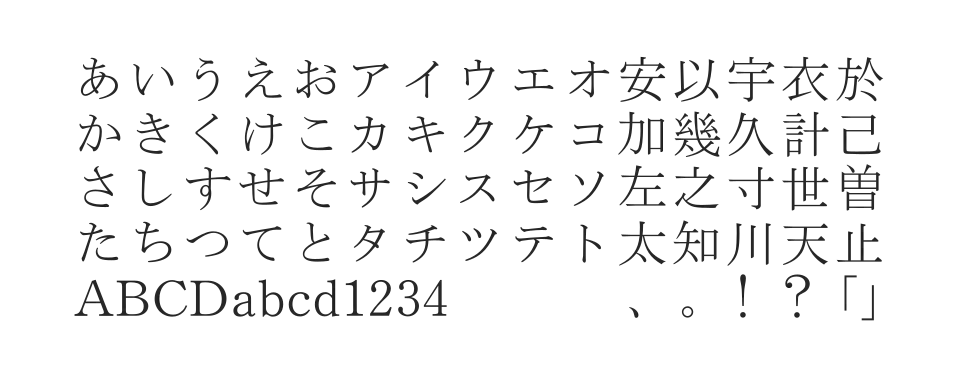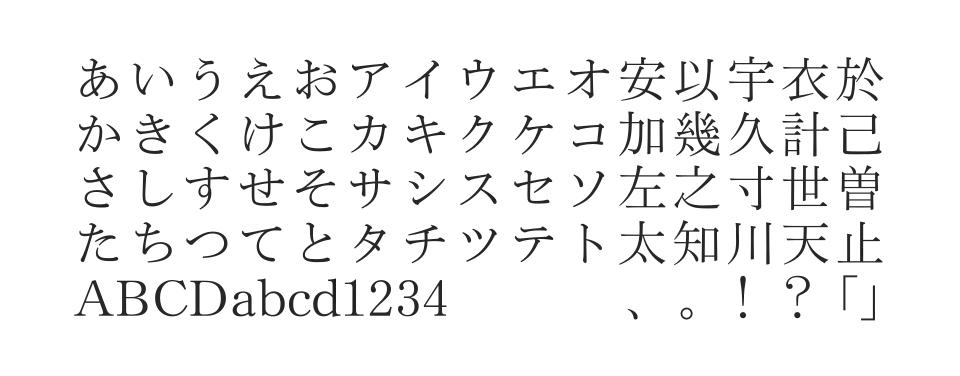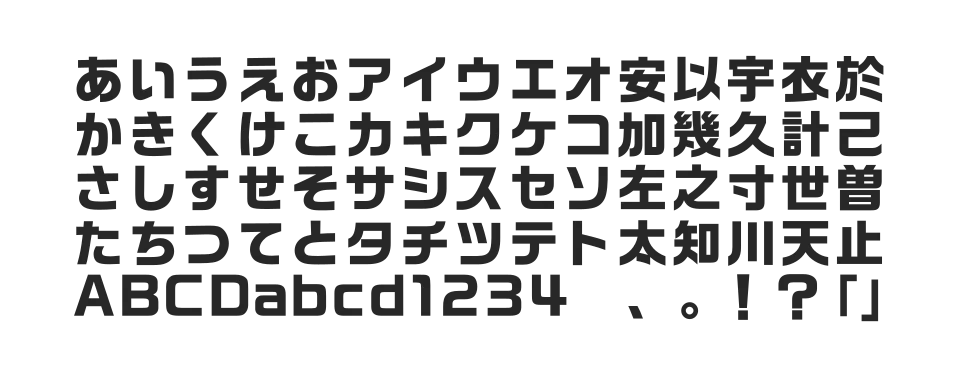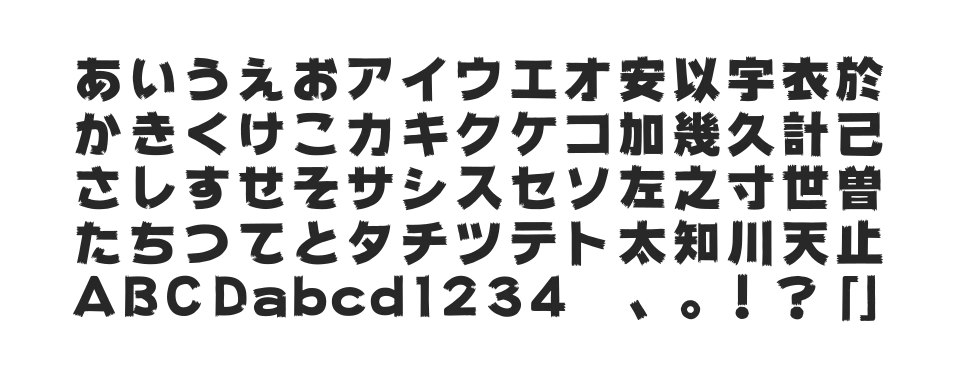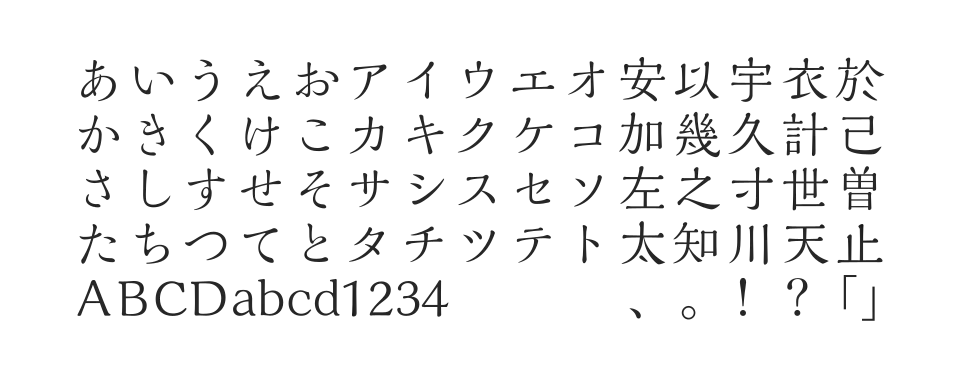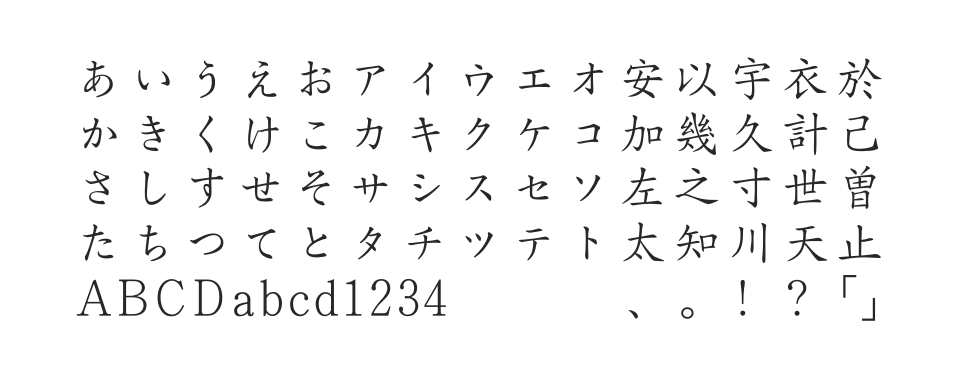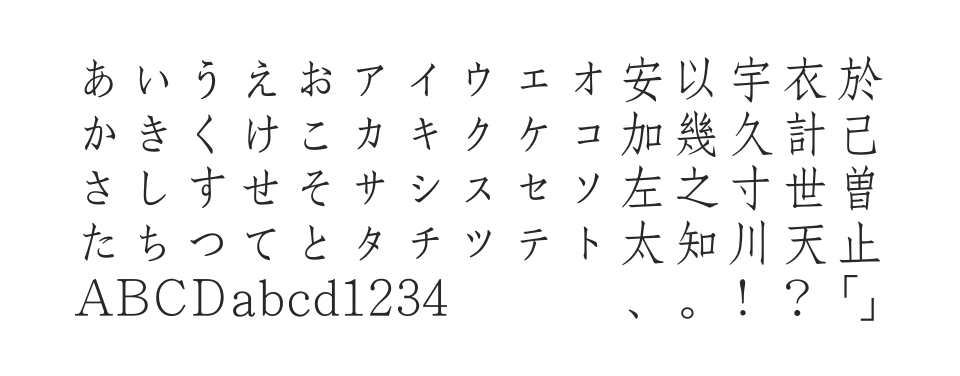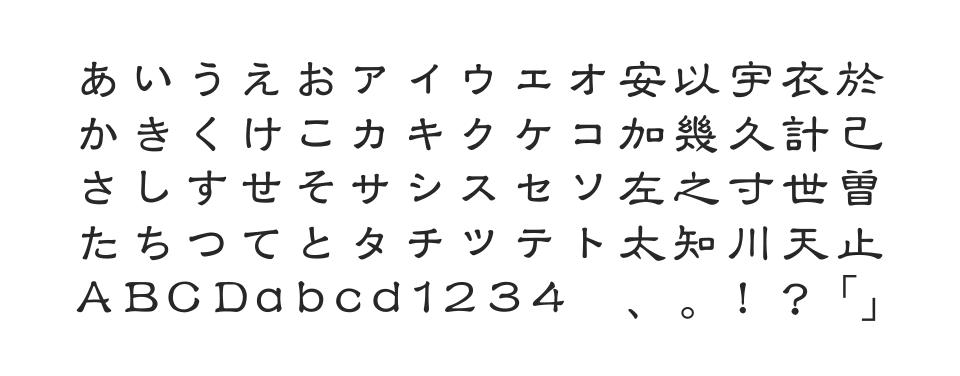
優しくリズミカルなカーブをもち、ソフトなイメージの表現に最適な丸ゴシック体。手書きのイメージを残し、読みやすさを考慮した文字の大きさで親しみやすいデザイン。
中国漢王朝を代表する正統な隷書体。文字形象が定着した伝統をおもくみ、新しい時代に対応できるデザイン。風化と風蝕をへてきた素朴で古拙感を漂わせる形象が特徴。
シャープなイメージを備える宋朝体。やや縦長の文字、力強い起筆、まげ・ハネの鋭さ、大ぶりで鋭角なハライの処理が特徴。本文書体をはじめ、名刺や案内状にも使用可能。
清王朝の康煕帝に源流を発する楷書体。端正かつ柔軟で、なめらかな筆の運びが特徴。明治期の木版印刷物に登場した流麗なかな字様を骨格の参考にした伝統書体シリーズ。
明朝体に隷書の筆法を取り入れた漢字と、活字時代の筆の運びを感じさせるかなをもったデザイン書体。明朝体の端麗な表情に隷書のハネ、ハライ、点画の特徴を織り交ぜた上品な文字。
始筆・終筆部に太いブラシで描いたような荒さを持たせた、フリーハンドスタイルのデザイン書体。素朴で親しみやすい雰囲気を醸し出す筆勢が特徴。
力強さと読みやすさを両立したデザイン書体。始筆・終筆部を水平・垂直に処理し、縦組み横組み両方で鮮明な文章ラインを実現するディスプレイ書体。
しなやかなカーブとキレのある直線を調和させた、可読性の高い本格派の本文用明朝体。小がなバリエーションでPr5仕様の20,317文字を収録。
しなやかなカーブとキレのある直線を調和させた、可読性の高い本格派の本文用明朝体。小がなバリエーションでPr5N仕様の20,317文字を収録。
しなやかなカーブとキレのある直線を調和させた、可読性の高い本格派の本文用明朝体。小がなバリエーションでPro仕様の15,444文字を収録。